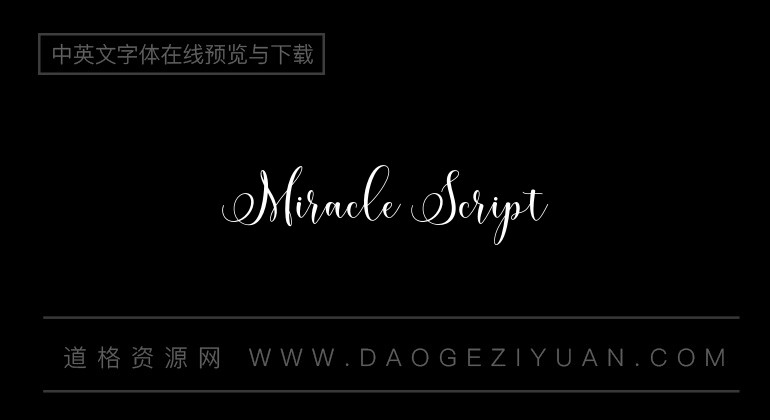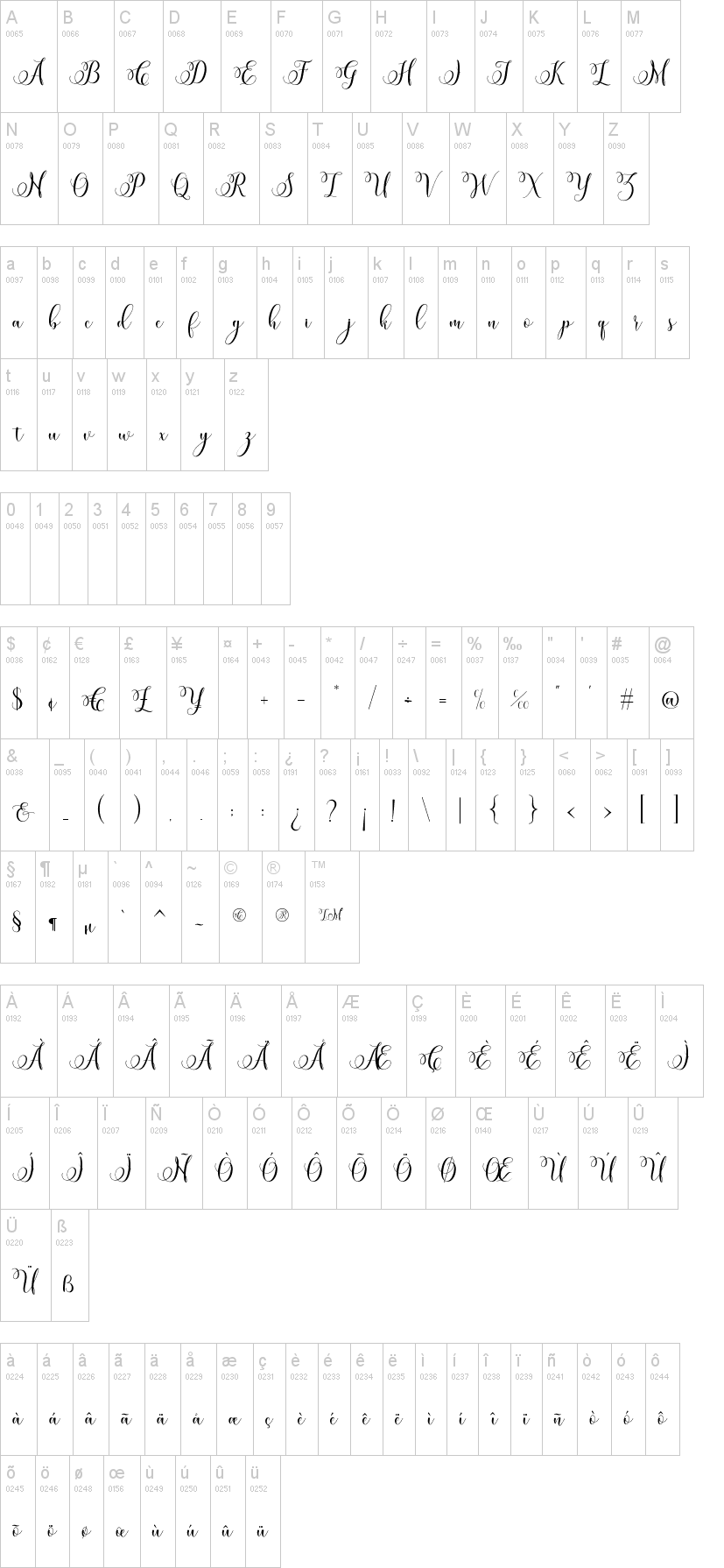
Miracle Script
Miracle Script 是一种手写风格的字体,它的笔画流畅、柔和,带有一定的装饰性和艺术性。该字体的设计灵感来自于手写字母,因此它有许多变化和不规则之处,使得它非常适合用于卡片、海报、广告、标志和其他需要个性化和艺术感的设计项目中。 Miracle Script 字体的特点包括: 1. 手写风格:该字体的每个字母都像是手写的,因此具有人性化和自然感。 2. 艺术性:Miracle Script 字体的每个笔画都是精心设计的,其中包括花卉、藤蔓和其他装饰性元素。 3. 可读性:尽管具有手写风格,但该字体的每个字母都很清晰易读。 4. 多种变体:Miracle Script 字体提供了多种变体,包括粗体、斜体、下划线和删除线等。 总之,Miracle Script 字体是一种非常独特的字体,它具有手写风格、艺术性和可读性,适合用于各种设计项目。
Miracle Script是一款非常不错的手写艺术字体,具有很好的视觉感,适合于文化类的宣传设计、商业类品牌的广告和产品包装设计以及个性化文字排版等较多场景。